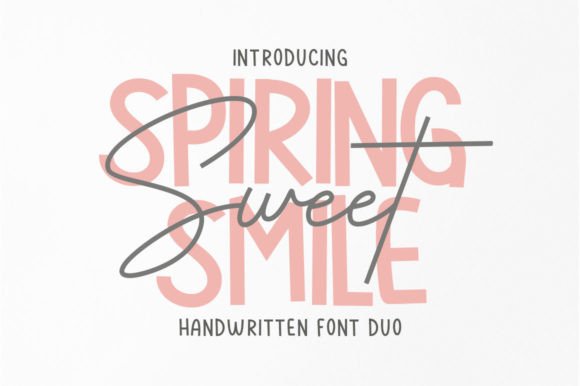
Spiring Smile Sweet
Jeśli szukasz wysokiej jakości materiałów, takich jak Spiring Smile Sweet, ten pakiet premium to fantastyczny wybór dla Twoich kreatywnych projektów.
Niezależnie od tego, czy tworzysz produkty POD (druk na żądanie), zaproszenia ślubne czy grafiki do mediów społecznościowych, Spiring Smile Sweet będzie idealnym wyborem.